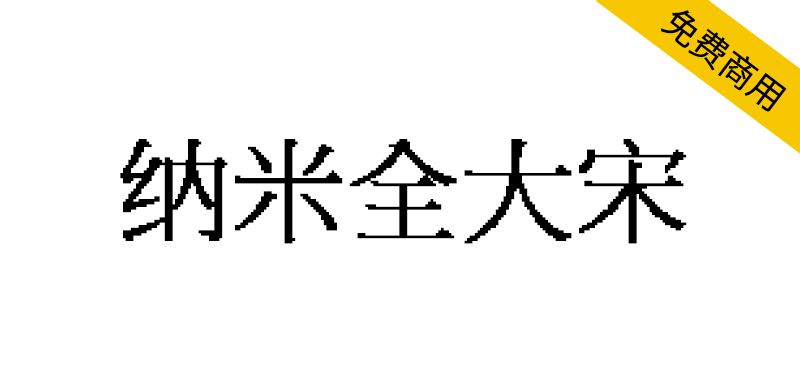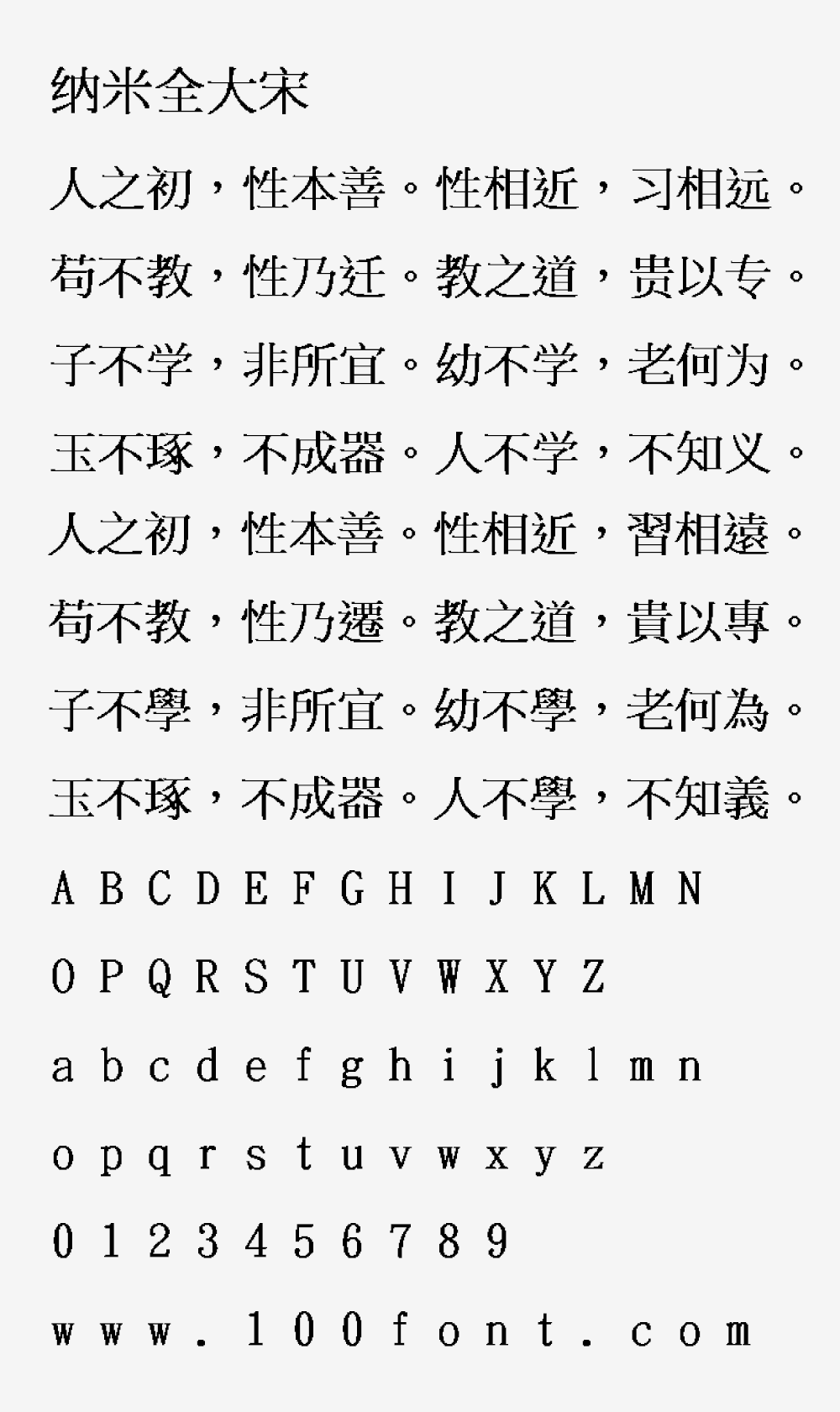
纳米全大宋(NanoQyoanDaSong)是一款以全字库正宋体作为基本进行像素制作的像素风格大字库宋体字体,44x44大小的字符加上泛中日韩的字符支持。
收录字形 表意文字区域 已经全部支持的区域:基本区、A区、B区,
收录字形 表意文字区域 不支持或部分支持的区域:C区、D区、E区、F区、G区、H区、I区、J区、兼容区、兼容补充区
收录字形 字符集 已经全部支持的区域:GB2312-80、GB12345、BIG5、GBK、通规(三级字以外)、CNS11643
收录字形 字符集 不支持或部分支持的区域:WENZHOU_DIALECT、通规(三级字)、GB18030-L2、GB18030-L3、ALL-CHUNOM